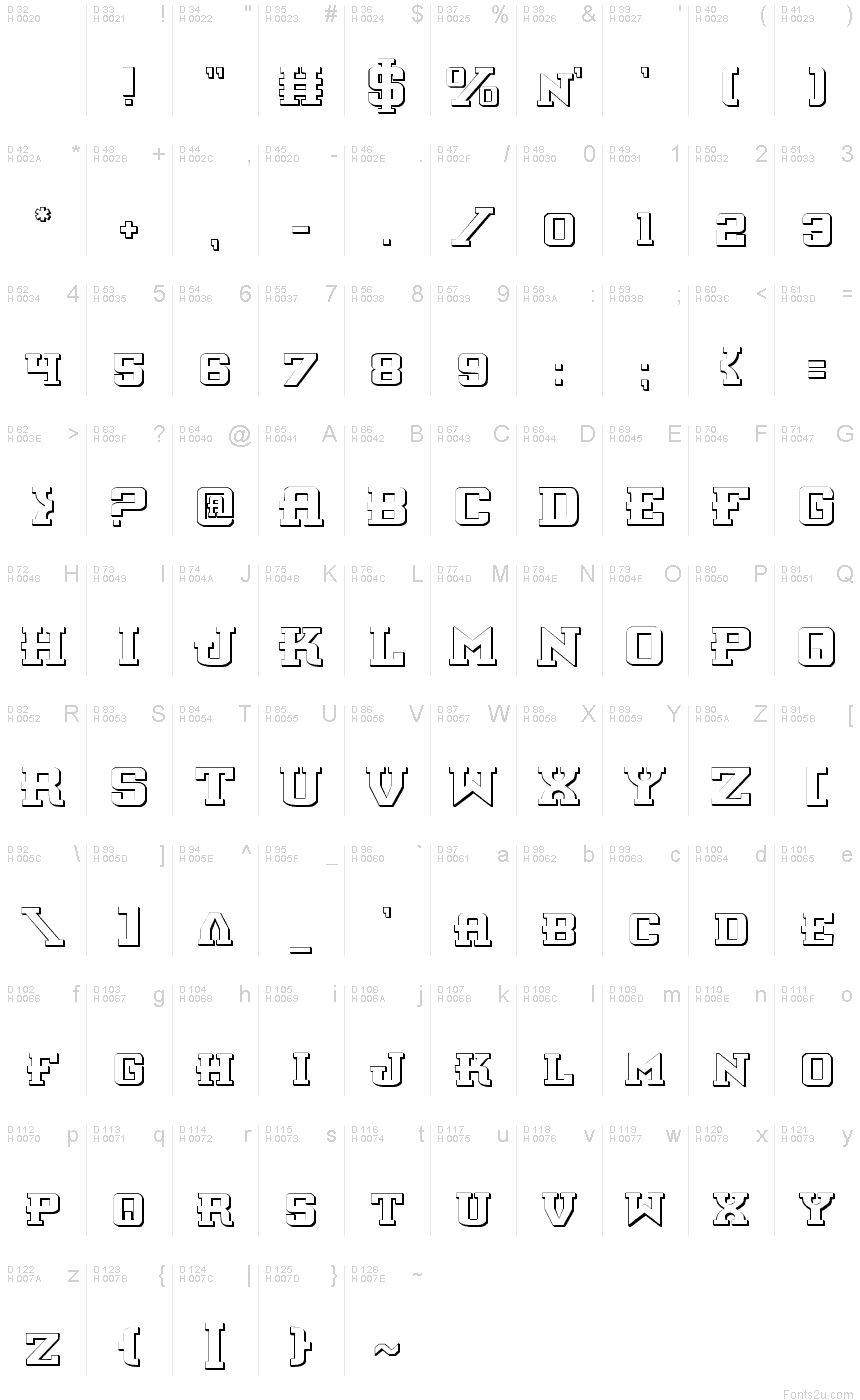
Interceptor Shadow od Iconian Fonts to darmowy, retro krój displayowy z wyrazistym obrysem, masywnymi wielkimi literami i klimatem starych plakatów. Litery są szerokie i pewne w wyrazie, a dzięki schodkowym narożnikom i cieniowanym krawędziom font sprawia wrażenie starego stempla lub zabytkowego szyldu, zamiast nowoczesnej, gładkiej czcionki.
Świetnie sprawdza się w brandingu sportowym, tytułach w stylu arcade, okładkach komiksów, logotypach typu odznaka czy ulotkach eventowych, gdzie krótkie słowa potrzebują masywnego, nostalgicznego charakteru. Jako darmowy font, idealnie nadaje się również do plansz tytułowych, monogramów i jako mocny akcent na gadżetach czy opakowaniach – zwłaszcza gdy chcesz, aby to obrys i cień stanowiły główny element dekoracyjny.
Interceptor Shadow